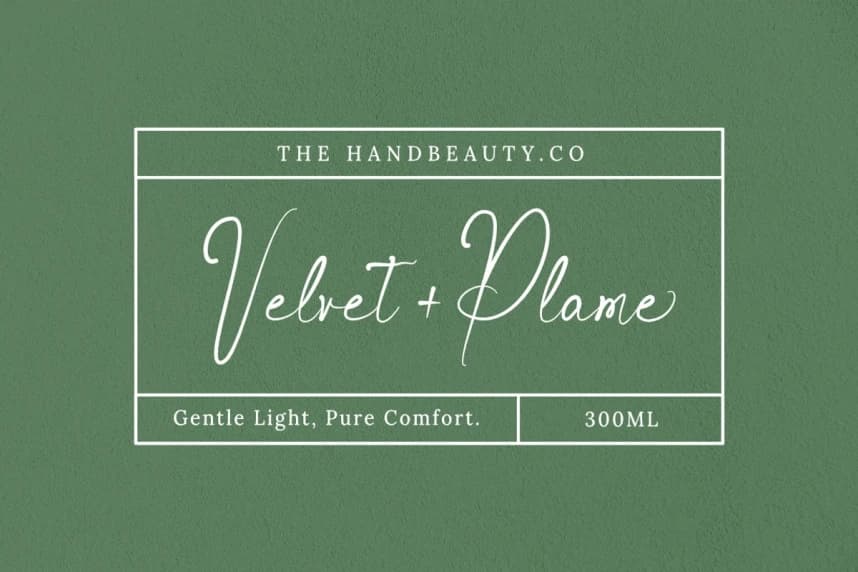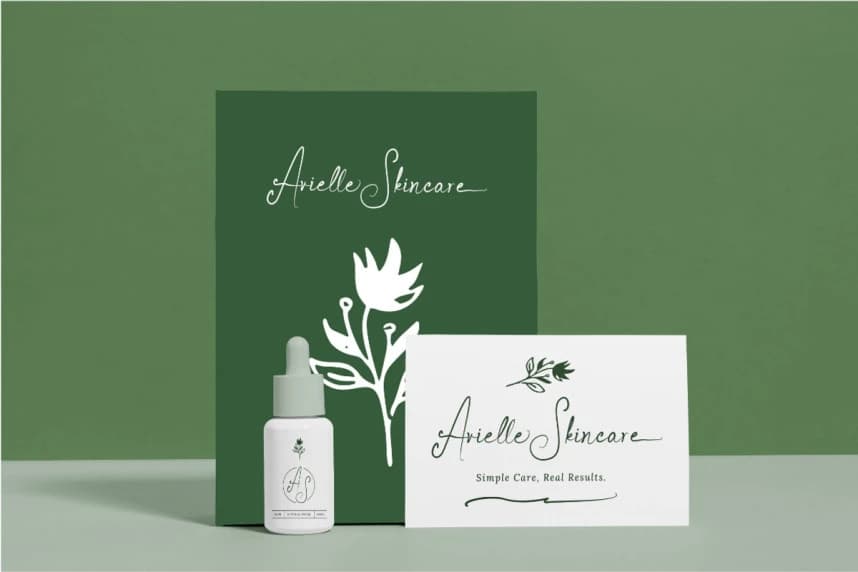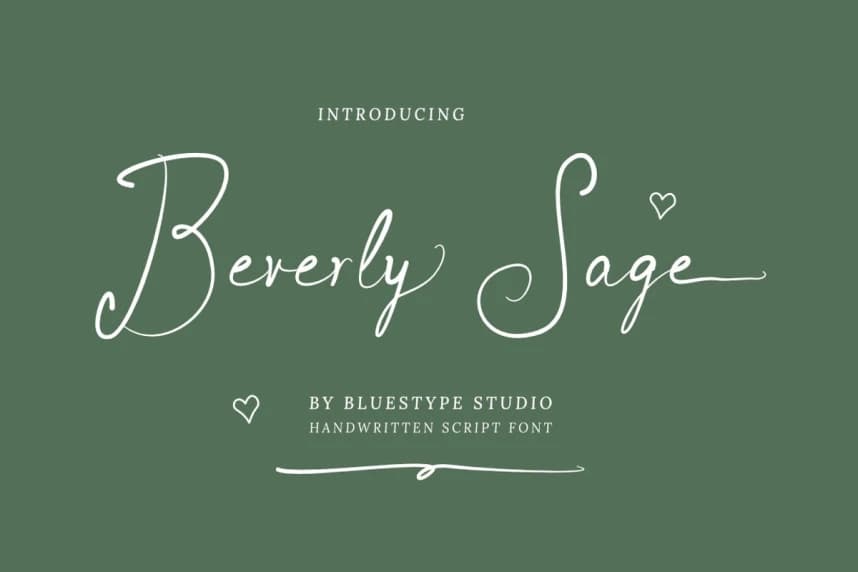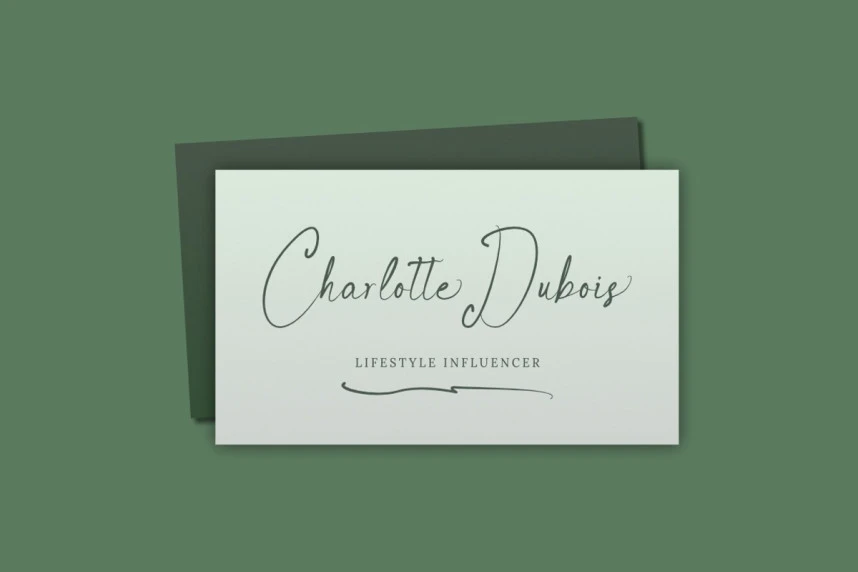
Beverly Sage Font, doğal ve oyuncu bir el yazısı fontudur; özgün, gerçek yaşamdan alınan el hareketlerinden ilham alınarak tasarlanmıştır. Her karakter, gerçek kalem-kağıt hareketinin kusurlu güzelliğini yakalar ve bu da projeler için kişisel, samimi ve eğlenceli bir estetik gerektirdiğinde mükemmel
Beverly Sage Font, doğal ve oyuncu bir el yazısı fontudur; otantik, gerçek yaşamdan ilham alan el hareketleriyle tasarlanmıştır. Her karakter, gerçek kalem-kağıt hareketlerinin kusurlu güzelliğini yakalar; bu da onu kişisel, ulaşılabilir ve oyunbaz bir estetik isteyen projeler için mükemmel bir tercih yapar.